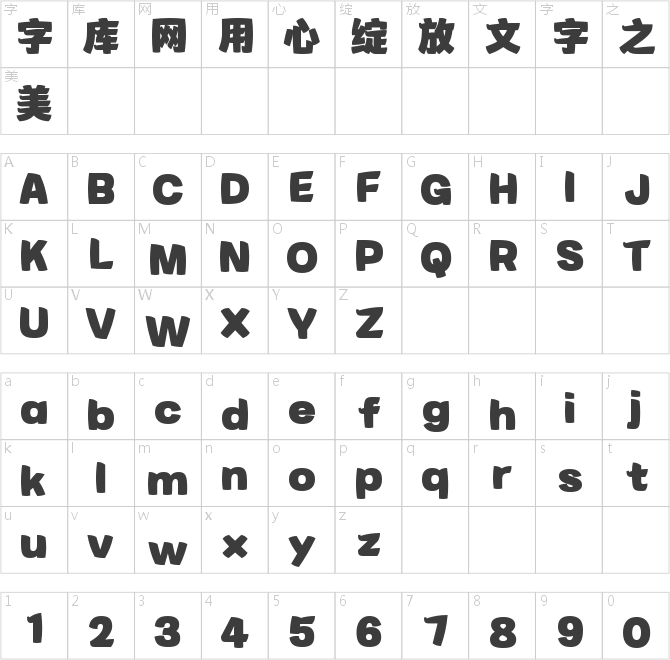
字體名稱: 字魂熊貓?bào)w
字魂熊貓?bào)w
字魂熊貓?bào)w介紹
字魂熊貓?bào)w字體字庫是一款讓人賞心悅目、百看不厭的中文字體,適合各類廣告和產(chǎn)品包裝設(shè)計(jì)應(yīng)用,字體大小5.28MB,格式為ttf字體,上傳用戶是瓜皮,作者/版權(quán)方為字魂